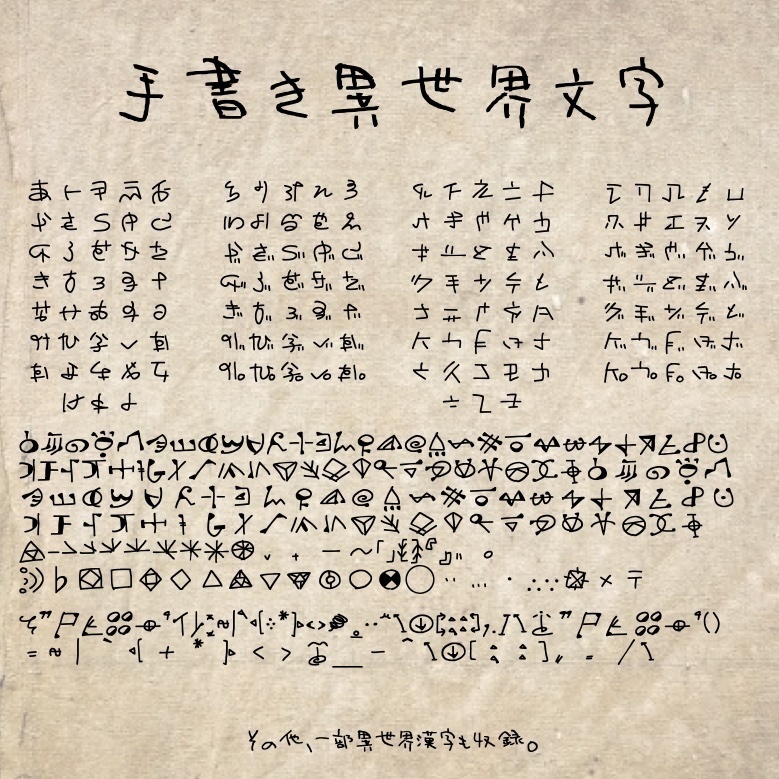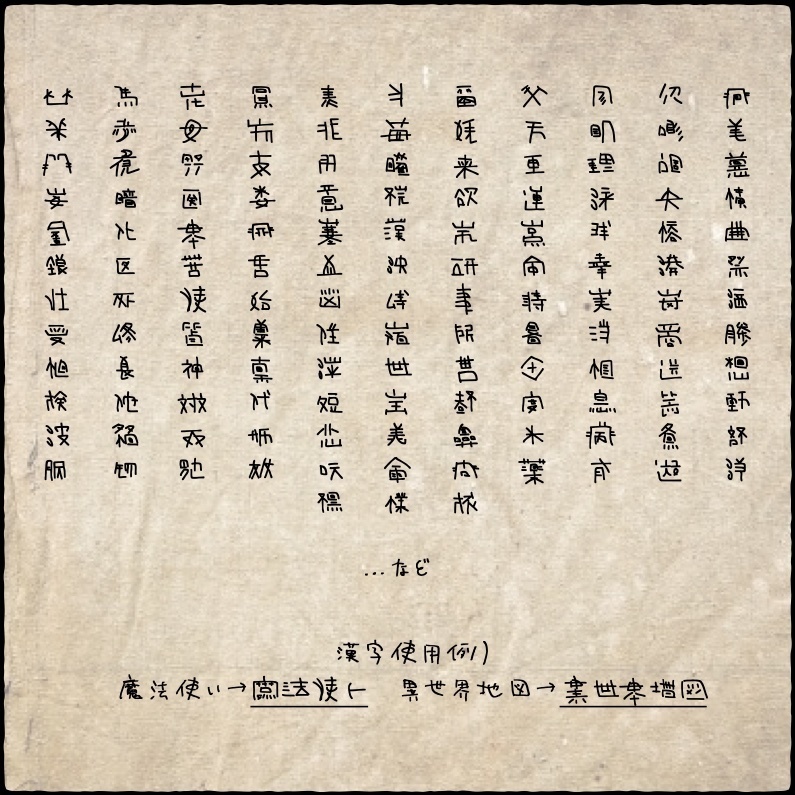
手書き異世界文字フォント
手書きのオリジナル異世界文字です。
✏️概要
手書きゆえに、文字の中心位置やサイズにバラツキがありますのでご了承ください。 本フォントの作成において、生成AIは使用しておりません。 意図せず現実世界の文字記号などと同一または類似して見えるものが含まれている可能性がありますが、特定の作品・文字体系を模倣、再現したり、権利を侵害する意図はありません。